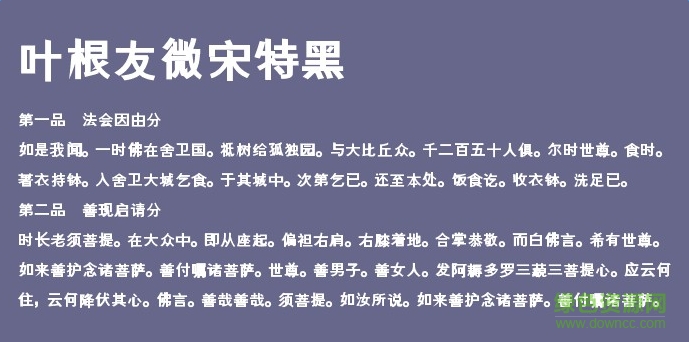
葉根友微宋特黑字體
葉根友微宋特黑字體是一款粗獷超黑風(fēng)格字體軟件,微宋特黑體是微黑系列中比較實(shí)用的一款字體,字體筆畫(huà)鏗鏘有力,整體效果十分醒目,適用于各大廣告標(biāo)題的書(shū)寫(xiě),還有更多好看字體歡迎來(lái)綠色資源網(wǎng)下載體驗(yàn)!
葉根友微宋特黑字體是一款以微宋字體為原形所設(shè)計(jì)的中文字體,此款字體字形筆畫(huà)均衡,識(shí)別性強(qiáng),端正大方,整體風(fēng)格出色。該字體適用于微宋設(shè)計(jì)、創(chuàng)意設(shè)計(jì)、藝術(shù)設(shè)計(jì)等方面!
經(jīng)小編測(cè)試使用,字體非常粗黑,十分醒目,用于聊天搞笑別有一番韻味,整體效果好看,文雅性十足,非常適合裝逼哦!!